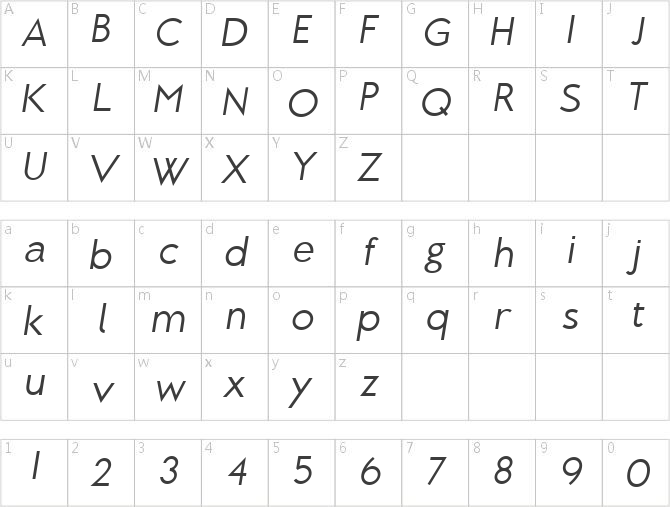
字體名稱: Brixton
Brixton-Book-Oblique
Brixton-Book-Oblique介紹
Brixton-Book-Oblique字體字庫是一款讓人賞心悅目、百看不厭的英文字體,適合各類廣告和產品包裝設計應用,字體大小0.04MB,格式為ttf字體,上傳用戶是/zyj【GF】,作者/版權方為未知